Граффити шрифты бесплатные и красивые (graffiti fonts)
В принципе, искать любые шрифты в интернете не так и сложно — просто заходите в Google и вбиваете нужное ключевое слово. Советую делать это на английском, так как вариантов найдете намного больше. Например для граффити шрифтов запрос будет «graffiti fonts» или еще лучше «free graffiti font», то есть бесплатные граффити шрифты. В итоге в поисковой выдаче будут представлены разные ссылки на крупные порталы со шрифтами или же статьи подборки лучших шрифтов. Проходите по ссылкам и скачиваете нужные вам варианты.
Marsneveneksk
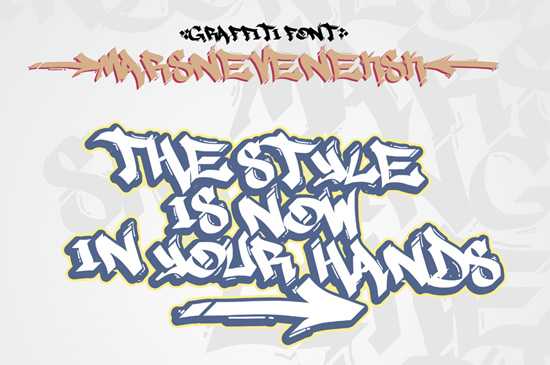
WildStyle
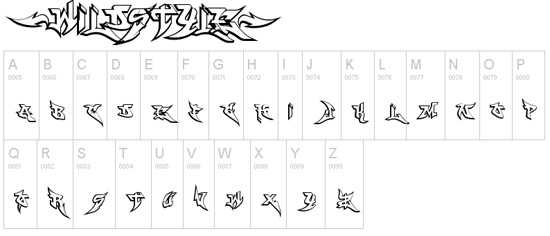
Stylin’ BRK
Graffogie
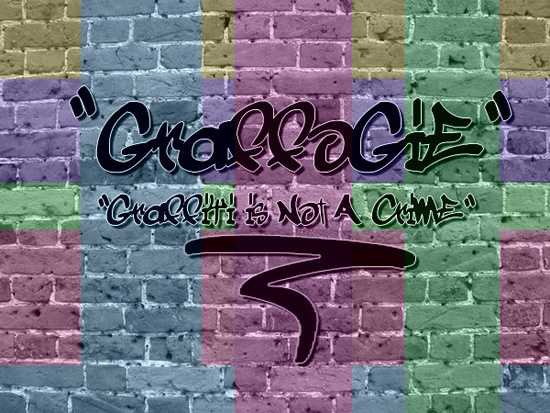
Most Wasted
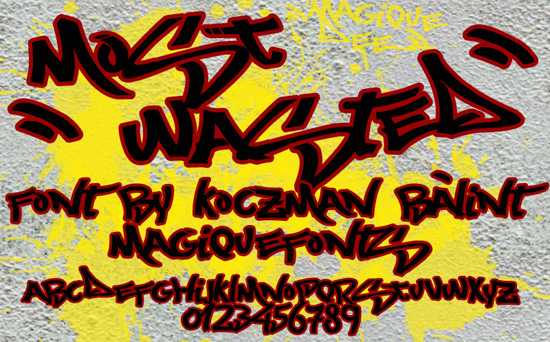
Street Writer
Searfont
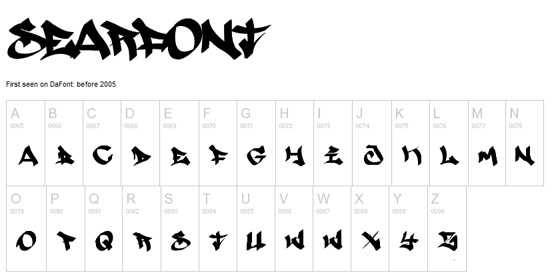
Ruthless One
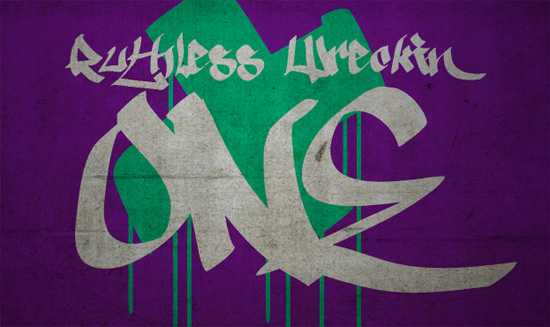
Degrassi
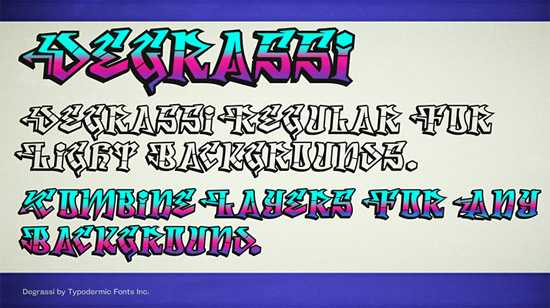
Throwupz
Кстати, при заходе на страницу шрифта вы сможете посмотреть как выглядит весь граффити алфавит и что представляет из себя каждая буква. В некоторых из них есть примеры использования граффити шрифта, что тоже весьма полезно дабы увидеть как смотрится надпись на практике. Поскольку иногда без добавления в фотошоп граффити шрифты смотрится обычными. Вот еще интересные варианты с того же Dafont.
Bored Schoolboy
Wassimo Graffiti
Urban Hook-Upz
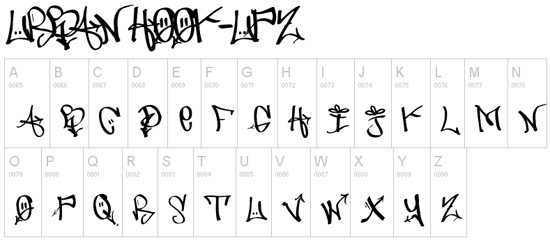
Brock165
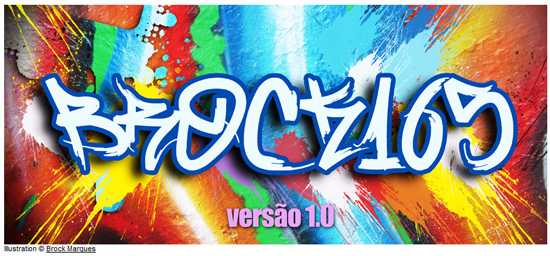
Rufa
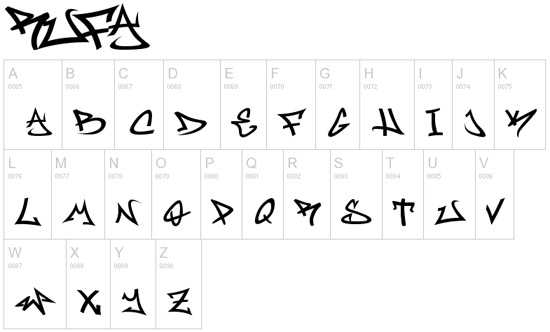
brushtip-C Font Family
kaliGraff Font Family
PWGraffiti Font
MAWNS’ Graffiti Filled Font
Dope Jam Font
Хотя на Dafont выбор граффити шрифтов гораздо больше и лучше. Есть в выдаче, кстати, и отдельные подборки с избранными фонтам точно такие, как я сейчас делаю. Плюс таких статей, что выбираются лучшие шрифты, а не все подряд. Автор, по сути, за вас делает все рутинную работу, просматривая десятки разных вариантов. Например, выше представлены 15 граффити шрифтов из 200 просмотренных на Dafont:)
Да, конечно, в таких подборках шрифтов автор может многое опустить, поэтому, если вы на нашли нужный вам вариант в статье, изучайте сайты-архивов.
El&font Block
The Graffiti Font
Brock Vandalo
A Dripping Marker
Juice
В поисках красивых граффити шрифтов для фотошопа я наткнулся на один интересный сайт — graffitifonts.com. Он целиком и полностью посвящен данному виду шрифтов и содержит много разной полезной информации. В дизайне найдете много граффити тегов, которые демонстрируют возможности тех или иных шрифтов. Это наглядно и удобно. Вот еще парочка материалов оттуда.
RapScript
GraffPity
Subway
5 Cent
Magik Marker
Итого отобрал для вас 30 граффити шрифтов алфавит которых подходит для рисования различных граффити тегов и урбанистических надписей. Конечно, тут еще многое зависит от сочетания цветовых решений, эффектов и фона. Если внимательно посмотреть на картинки шрифтов, то обычные списка букв алфавита не особо впечатляют, а вот реальные примеры их использования совсем наоборот.
Кириллические русские граффити шрифты для фотошопа
На страницах блога ранее уже была подборка с оригинальными бесплатными graffiti fonts, и стало интересно как много удастся найти отечественных наработок. К сожалению, выполнить эту задачу, зачастую не так легко, как хотелось, поскольку их количество весьма ограничено. Отличный тому пример — тематические русские машинописные шрифты, где материалов на латинице в три раза больше.
Тем не менее, подобные наборы для наших дизайнеров достаточно востребованы. Поэтому в процессе поиска приходится слегка «импровизировать» и вместо каких-то тематических, например, праздничных/поздравительных искать необычные рукописные шрифты. С этим в очередной раз пришлось столкнуться, когда мы решили подобрать кириллические граффити шрифты для фотошопа.
Sprite Graffiti Font